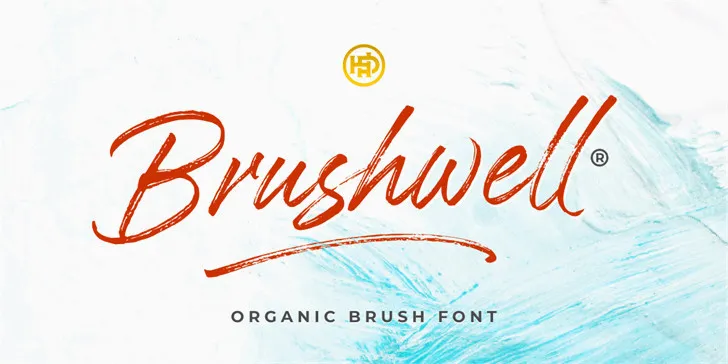
Descubra a versão atualizada do Brushwell Font, uma elegante fonte brush script, perfeita para personalizar sua identidade visual. Esta fonte é resultante de um estilo cuidadosamente elaborado através de escrita a mão com uma ferramenta de escrever que não é muito macia nem muito dura. O resultado é um design refinado e feminino, com texturas naturais e um tamanho fino ideal para combinar harmoniosamente em sua próxima projeto. Introduzindo-se neste formato Script Font, o Brushwell Font surge da criatividade de hptypework. Perfeitamente adequada a uma variedade de aplicativos gráficos, incluindo assinaturas, cartões de estação, logotipos, textos de citação e capas para revistas ou livros, esta fonte é também perfeita para cabeçalhos de websites, roupas, marcas de marca e embalagens. Com seu aspecto cuidadosamente elaborado, o Brushwell Font oferece uma textura que transmite sutileza e feminilidade. Seja em sua próxima campanha ou no layout de um livro, este design é perfeito para manter a consistência estética da sua marca. Atraente e sofisticada, esta fonte é ideal para quem procura algo único na sua paleta de recursos gráficos.